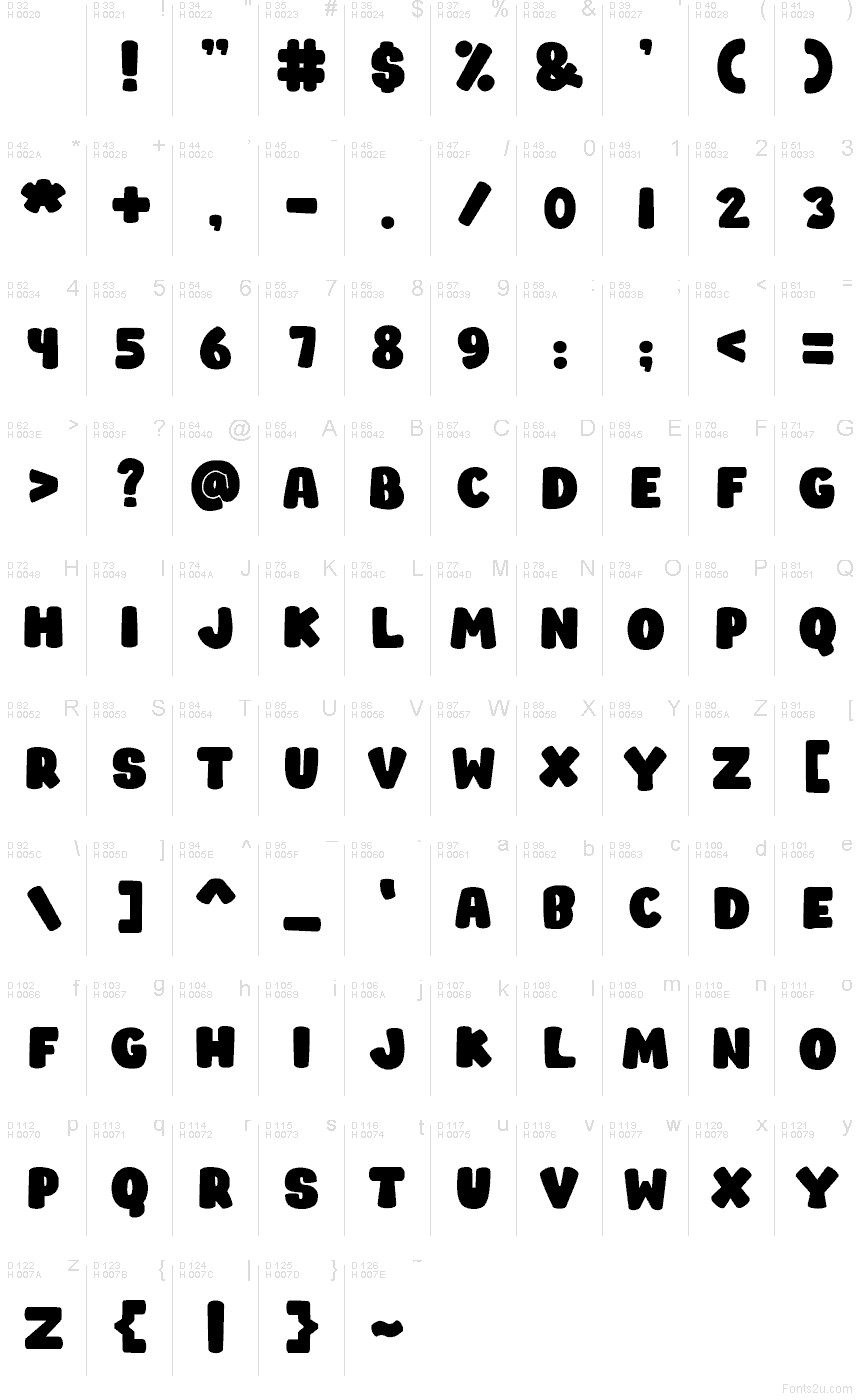
Písmo Teebald od Tokokoo je bezplatný font ve stylu cartoon s kulatými, blokovými tvary a měkkými okraji. Jeho znaky působí nadýchaně a přátelsky, s širokými křivkami, čtvercovými rameny a výrazným, ručně kresleným rytmem, který si udržuje živost bez zbytečného chaosu.
Teebald skvěle funguje na obálkách dětských knih, titulech komiksů, záhlavích plakátů, logách, obalech a grafice pro sociální sítě, protože jeho tvary přinášejí odvážnou a neformální přítomnost. Tento bezplatný font se také hodí pro samolepky a krátké propagační texty, kde hledáte kulaté písmo, které je zábavné, čitelné a snadno se stylově doplňuje jasnými barvami nebo konturami.